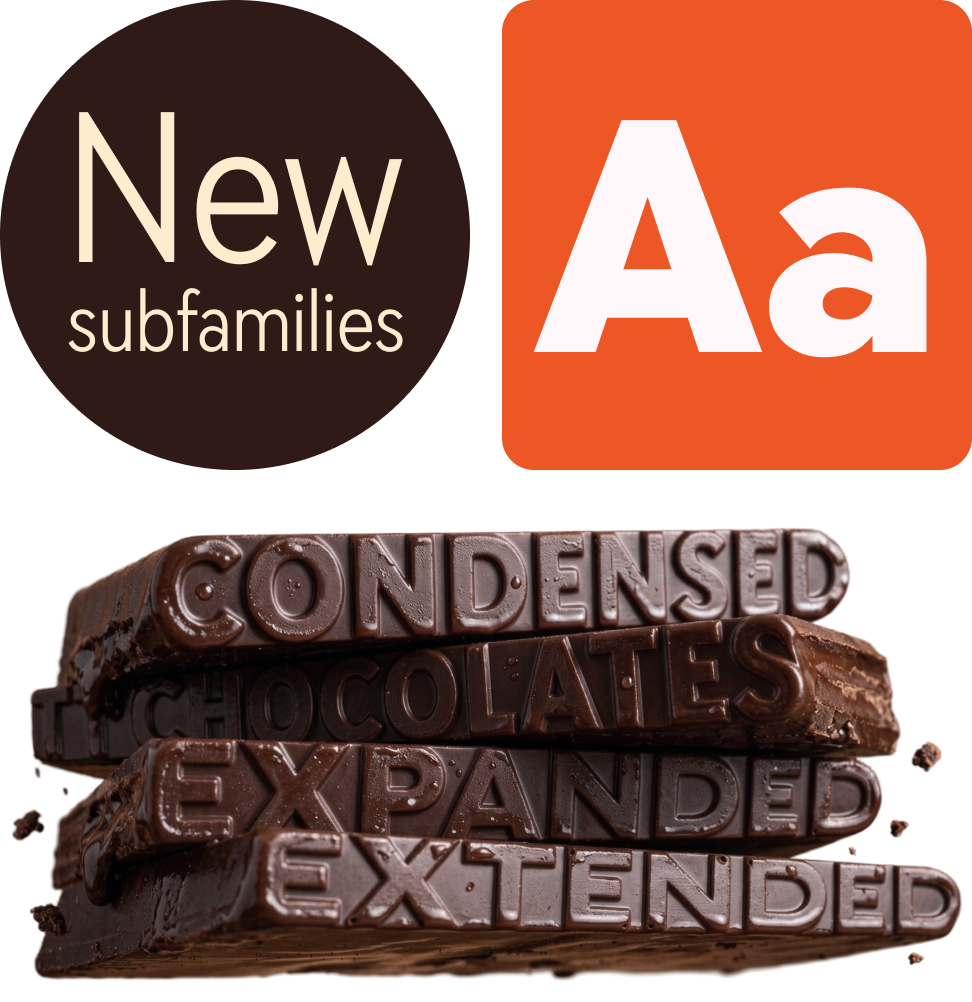
Las 10 mejores fuentes para diseños de carteles
La creación de carteles es un enorme campo creativo para trabajar con tipografía. Pero, ¿cómo elegir la fuente de póster adecuada para que tu idea no se pierda? ¿Qué fuentes existen para los carteles y cómo sabes cuál necesitas? ¡Te lo contamos en este artículo!
¿Por qué es importante la elección de la fuente para los carteles?
La fuente es una parte integral de cualquier cartel. Ya sea un cartel para un evento cultural o deportivo, un periódico estudiantil, un cartel publicitario o propagandístico, cada uno de ellos contiene texto que ayuda a transmitir un mensaje particular.
¿Por qué es importante la elección de la fuente para los carteles?
Además, en algunos carteles la tipografía pasa a primer plano y los elementos gráficos solo complementan la inscripción o están completamente ausentes; hablaremos de esto con más detalle a continuación.
Por lo tanto, es obvio que para crear un cartel espectacular y elegante que llame la atención y transmita correctamente su idea, es importante elegir la fuente adecuada.
Fuentes de carteles: tipos
Primero, averigüemos qué fuentes existen para carteles. Todas las fuentes se pueden dividir en dos grupos: visualización y texto.
Las fuentes de visualización son fuentes que se utilizan para acentos: se pueden utilizar para diseñar un título, es decir, cualquier inscripción grande que llame la atención. Estas fuentes tienen un carácter pronunciado, gráficos más complejos y muchos detalles interesantes y, por lo tanto, están diseñadas para su uso en tamaños grandes y medianos y funcionan muy bien en carteles, incluso solas, sin elementos gráficos adicionales. En tamaños pequeños son difíciles de leer.
Las fuentes de texto vienen al rescate cuando necesitas una fuente que sea fácil de leer en un tamaño pequeño. Se trata de fuentes más neutras con gráficos simples que no llaman la atención y son fáciles de percibir visualmente. Esto no significa que dichas fuentes no puedan usarse en tamaños de fuente grandes y colocarse en primer plano en los carteles. Esto puede e incluso debe hacerse en los casos en que se desee lograr concisión y «pureza» del diseño, para crear un cartel minimalista.
Resulta que casi cualquier fuente se puede utilizar para un póster. Averigüemos cómo elegir el que más le convenga.
Cómo elegir la fuente adecuada para un póster: lista de verificación
De cara al futuro, digamos que estos consejos deben tomarse como apoyo a la hora de elegir y no como instrucciones claras. Después de todo, al crear un cartel, la tipografía a menudo se convierte en la principal herramienta creativa del diseñador, permitiéndole crear algo único y hermoso. Así que no tengas miedo de experimentar y probar diferentes opciones de fuentes. Para ello, puedes descargar sus versiones de prueba de forma gratuita.
Determina cuál es la idea de tu cartel
Primero, debe comprender para qué servirá su póster: ¿informativo o decorativo? ¿Publicidad o promoción? ¿De qué humor estará? ¿Qué combinación de colores? ¿Será brillante o minimalista? Habiendo respondido estas preguntas, elija una fuente de la categoría estilística que coincida con su diseño. La mejor fuente para carteles es aquella que ayuda a transmitir su mensaje.
Determinar el lugar y la función de la fuente en un diseño.
Ahora vale la pena pensar cómo usarás exactamente la fuente en tu póster. ¿Se limitará a complementar los gráficos o llamará la atención además del dibujo? ¿O tal vez el texto se convertirá en el elemento principal y único de tu cartel?
Si utiliza una fuente grande junto con gráficos, preste atención a los detalles: ciertos elementos de los caracteres de la fuente se pueden resaltar usando gráficos o se pueden encontrar similitudes entre ellos. Si está utilizando una sola fuente, intente experimentar con el tamaño y el peso en puntos para crear un diseño interesante para las letras. Si necesitas una fuente de texto con la que escribirás la inscripción en el cartel en tamaño pequeño, pasa al siguiente punto.
La legibilidad es importante
Las fuentes que se utilizan en un tamaño pequeño deben, ante todo, ser legibles. Para ello, deben cumplir los siguientes criterios: sencillez, claridad, proporciones neutras, anchura media de los caracteres y grosor de las líneas, ausencia de elementos decorativos. Lea más sobre cómo elegir una buena fuente de texto aquí.
La funcionalidad debe coincidir con las tareas.
Otro factor importante a la hora de elegir una fuente para un póster es su funcionalidad. Antes de elegir una fuente en particular, vale la pena comprender qué funciones necesita. Quizás su cartel no tenga una sola inscripción, sino muchas, todas en diferentes idiomas. Por lo tanto, debes asegurarte de que los auriculares admitan todos estos idiomas. Si desea utilizar diferentes fuentes en un póster o hacer una serie de carteles con el mismo estilo, elija tipos de letra con una gran cantidad de estilos. Una gran ventaja será la presencia de una fuente variable en el tipo de letra; de esta manera podrá experimentar con la tipografía y encontrar soluciones interesantes.